信息量巨大的版面编排法
相信刚接触设计或者工作时间不长的设计师,多多少少都会遇到各种各样的编排问题。今天这篇文章就是源于一位设计师提出的问题,他说:“当文案信息较多时要如何编排,版面看上去才能美观一些”。我相信大部分人都遇到过类似的情况,为此我收集了不少相关的设计作品,从中也总结出了一些编排的方法分享给大家。
不过编排方法部分我放在了文章的最后,因为在编排前还有不少细节要注意,下面我就带着大家先从最基本的建立页面开始逐步过渡到编排。
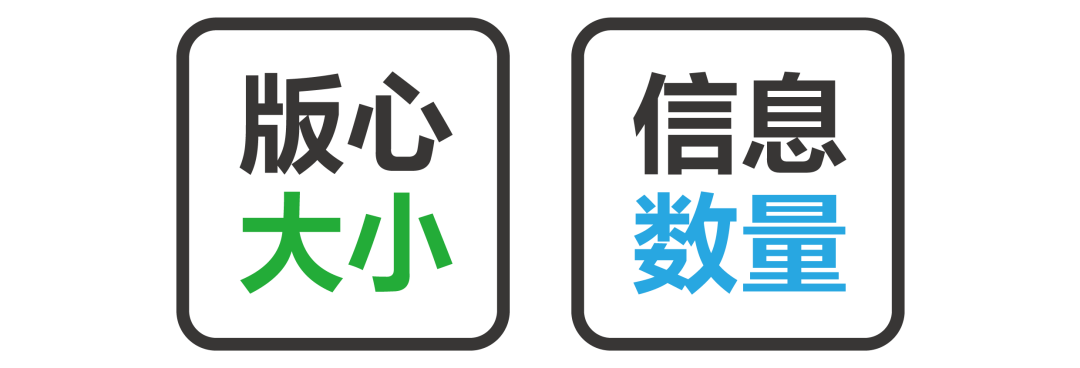
在我们订阅号之前的文章中提到过这样一个观点:版面是承载信息的一个载体。而一个版面承载信息的数量,完全取决于版心的大小。想要放下大量的信息,版心一定要大。但到底要多大才合适呢?
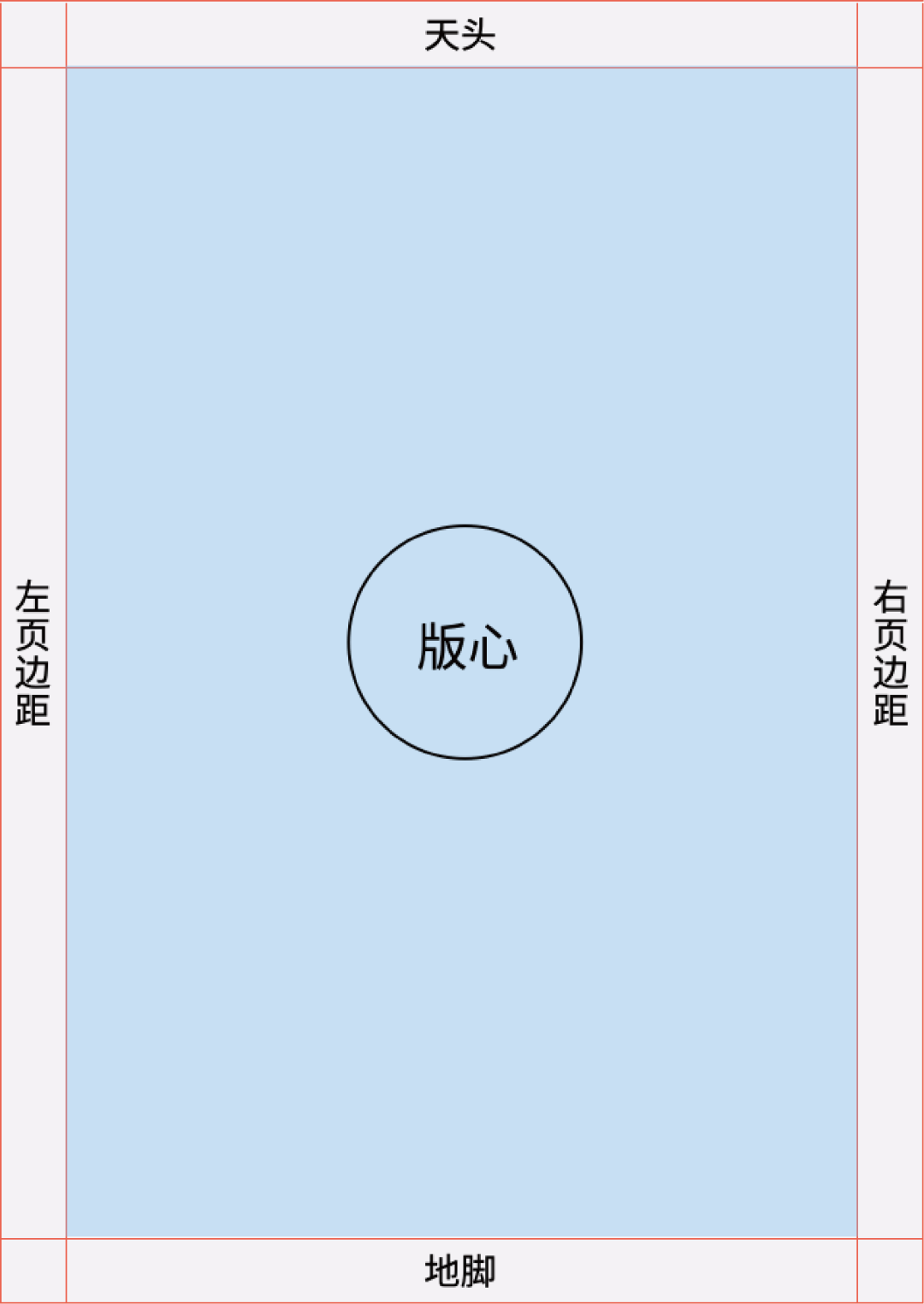
除去天头地脚、左右页边距以外,剩下的空间就是版心所在的区域。也就是说确定好天头地脚,左右页边距后版心就被确定好了。
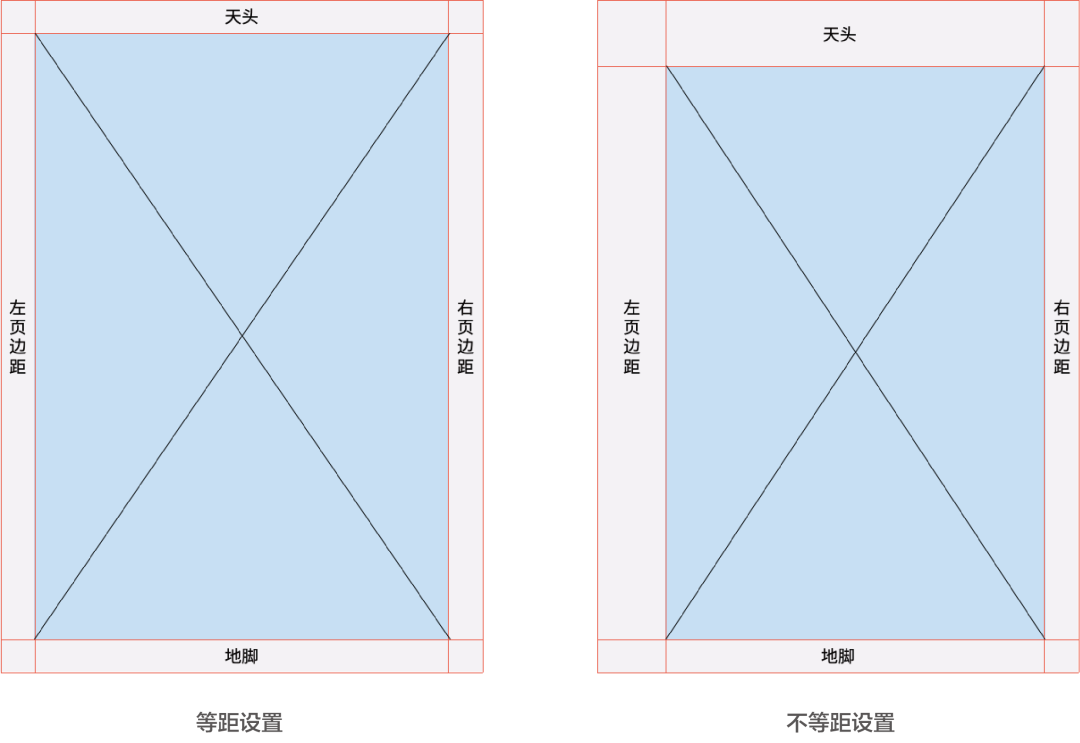
设定页边距的方式有两种,第一种是:等距设置,也就是天头地脚、左右页边距的大小都是相同的。第二种是:不等距设置,天头有可能大于地脚,左页边距也可能大于右页边距。而在这两种设置方法中,等距设置是最常用的。
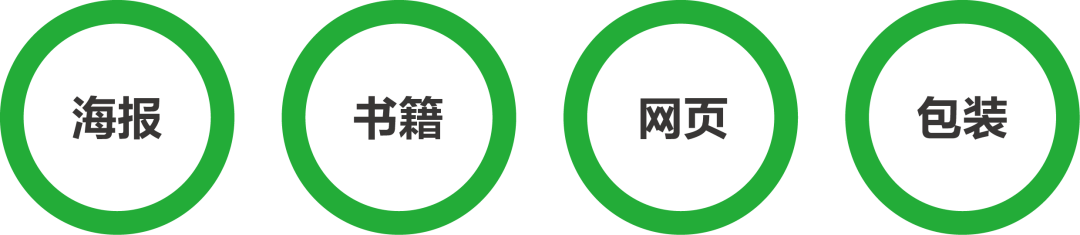
不管是在海报、书籍、网页还是包装中,等距设置都会让版面看起来非常稳定。所以在设定页边距时,四边的大小最好是一致的;尤其是左右页边距。因为,如果左右页边距设定的不一样,版面很有可能会出现重心不稳的情况。
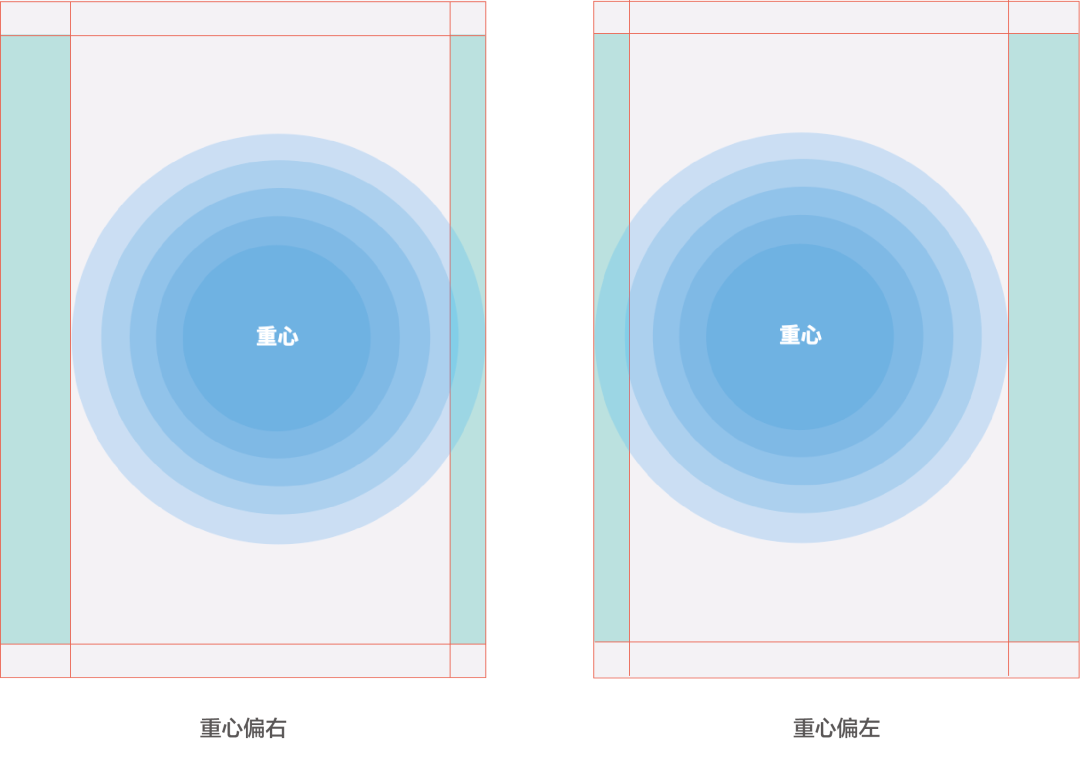
当左页边距大于右页边距时,重心可能会偏向右边。同理,当右页边距大于左页边距时,重心就可能会偏向左边。
不过存在即合理,虽然不等距设置会使版面重心变得不稳。但利用这个特性故意将天头地脚、左右页边距设置得不一样时,也能给版面带来动感。
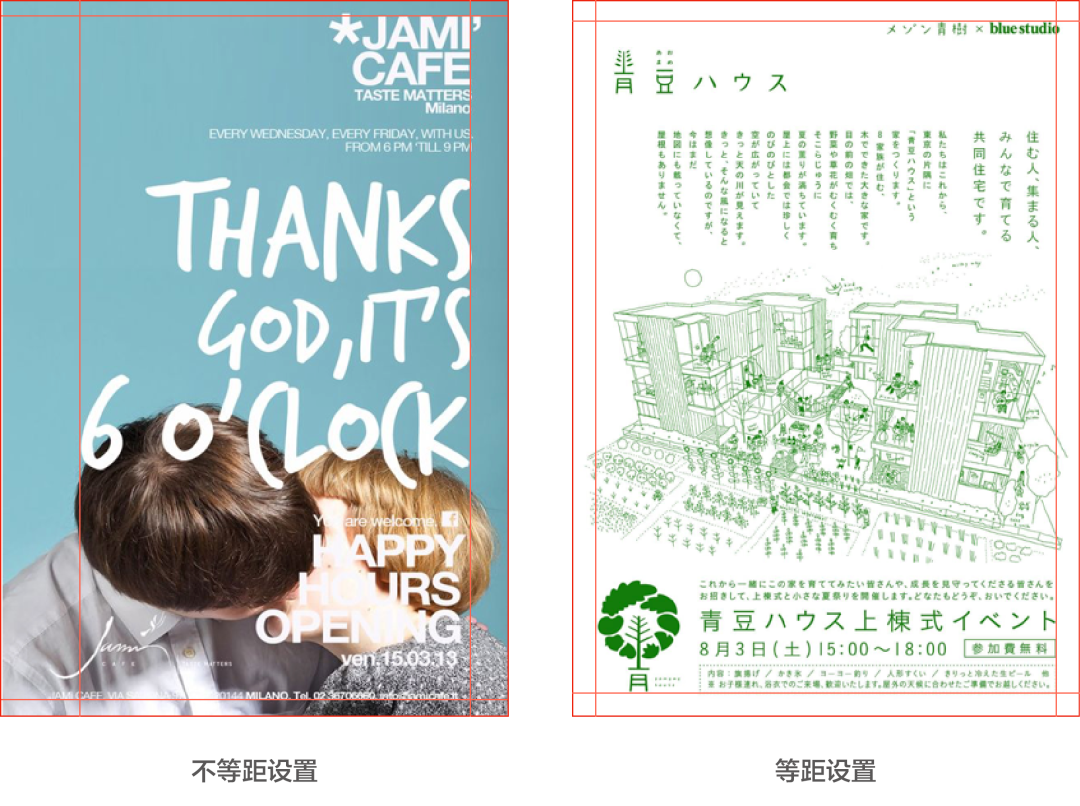
我们来看这组对比,左边的两幅海报明显是不等距设置,跟右边的等距设置相比,左边的海报少了四四方方的平稳感,却多了一些随意又轻松的活跃感。
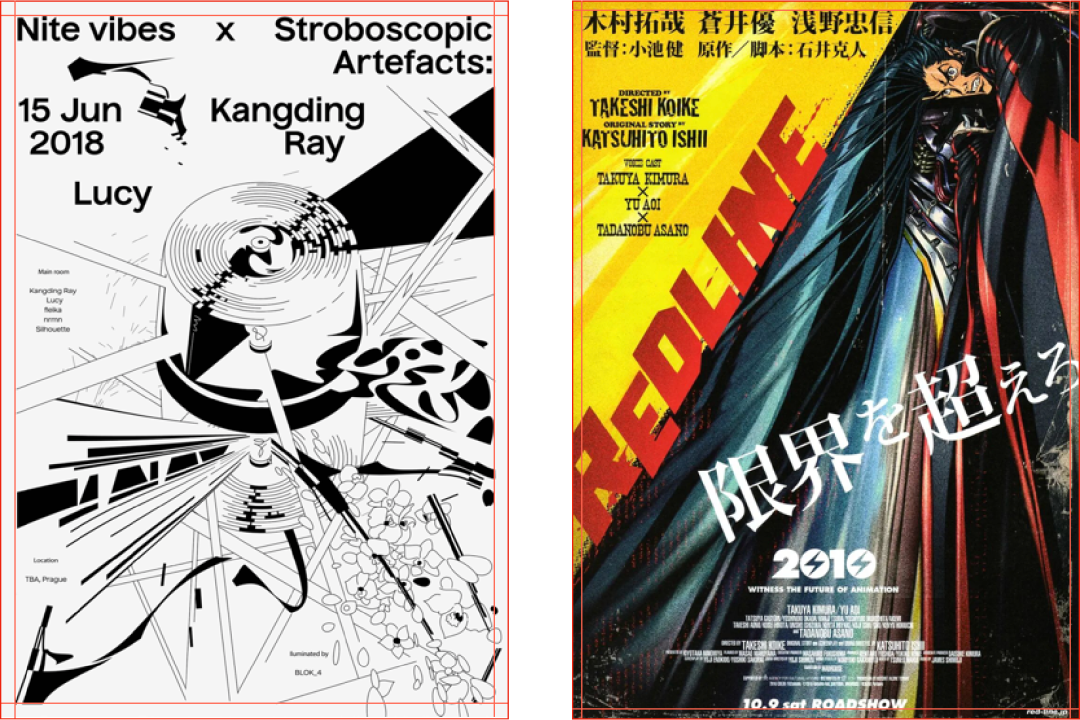
但是也不能以偏概全,因为即便是等距设置的版面也同样可以做出动感,比如现在我们看到的这些海报就是很好的例子。画面给人带来什么样的印象,取决于版面的编排方式,而不等距设置只是众多方法中的一种而已。
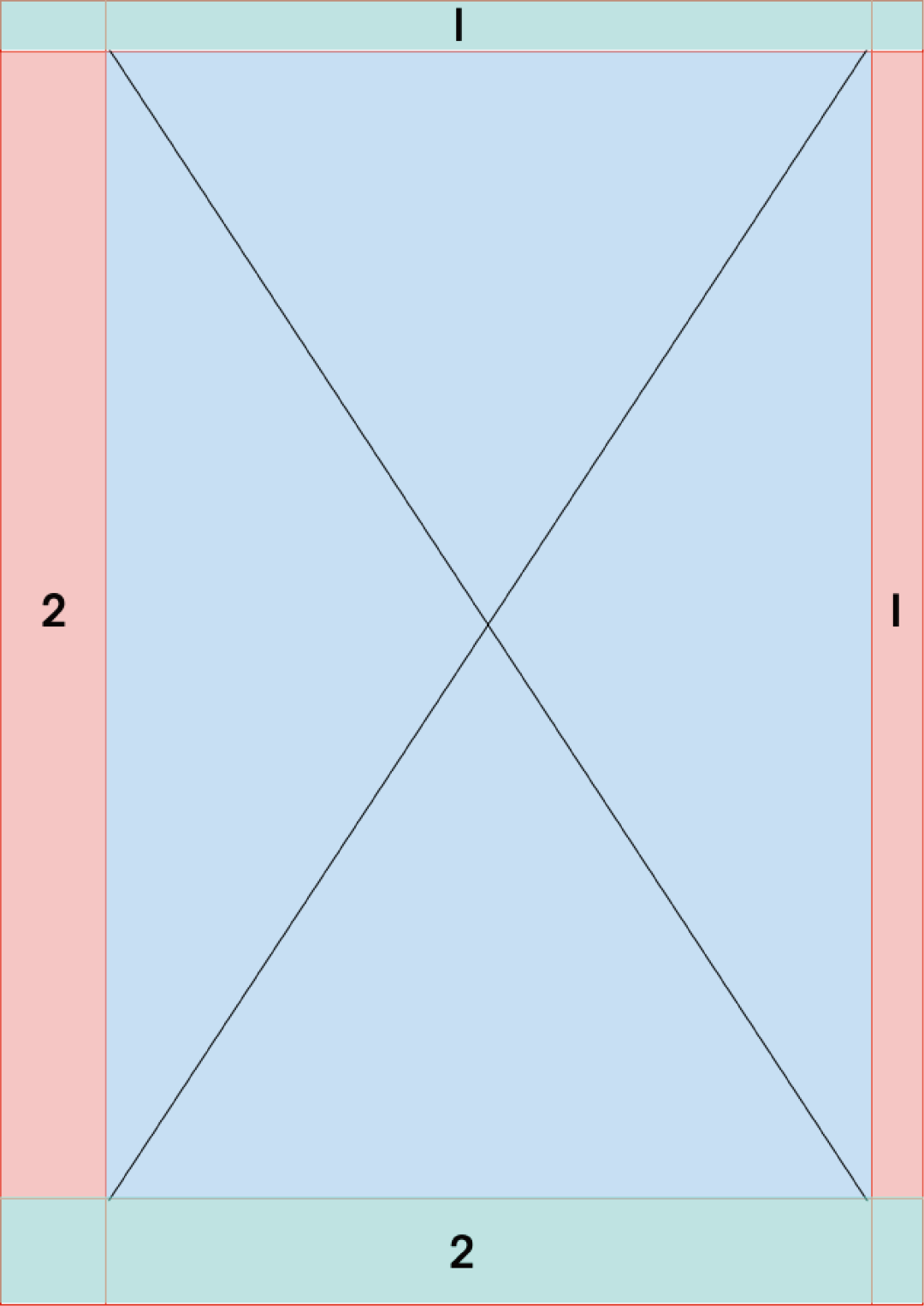
在实际操作中设定不等距的页边距时,可以用一个边的大小做参考,然后其他三边都与它呈一定的倍率关系。假设我们以天头作为参考,将它的边距设为为1,地脚可以是天头的2倍,也就是2。左页边距也可以是天头的2倍。右页边距可以是天头的1倍,也就是等于天头的大小。
虽然边距的大小可以自由设置,但是如果没有一个参考标准的话,一开始可能会无从下手,所以接下来我会根据不同尺寸的版面、文字数量的多少,列举出一些标准的页边距数值,供大家参考使用。当然在实际操作中,如果发现有不合适的地方,可以根据具体的需求来做调整。
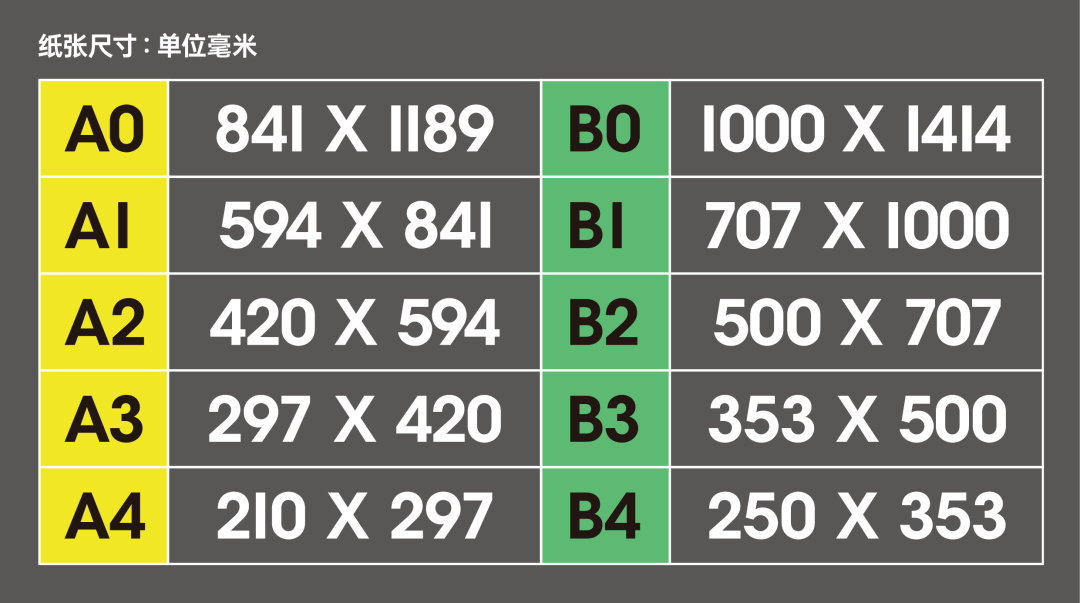
这是我们常用的纸张规格:A0-A4、B0-B4。有一点要跟大家说明的是,不管是从A0-A4还是B0-B4,它们只是纸张大小发生变化,而长宽比例是不变的。
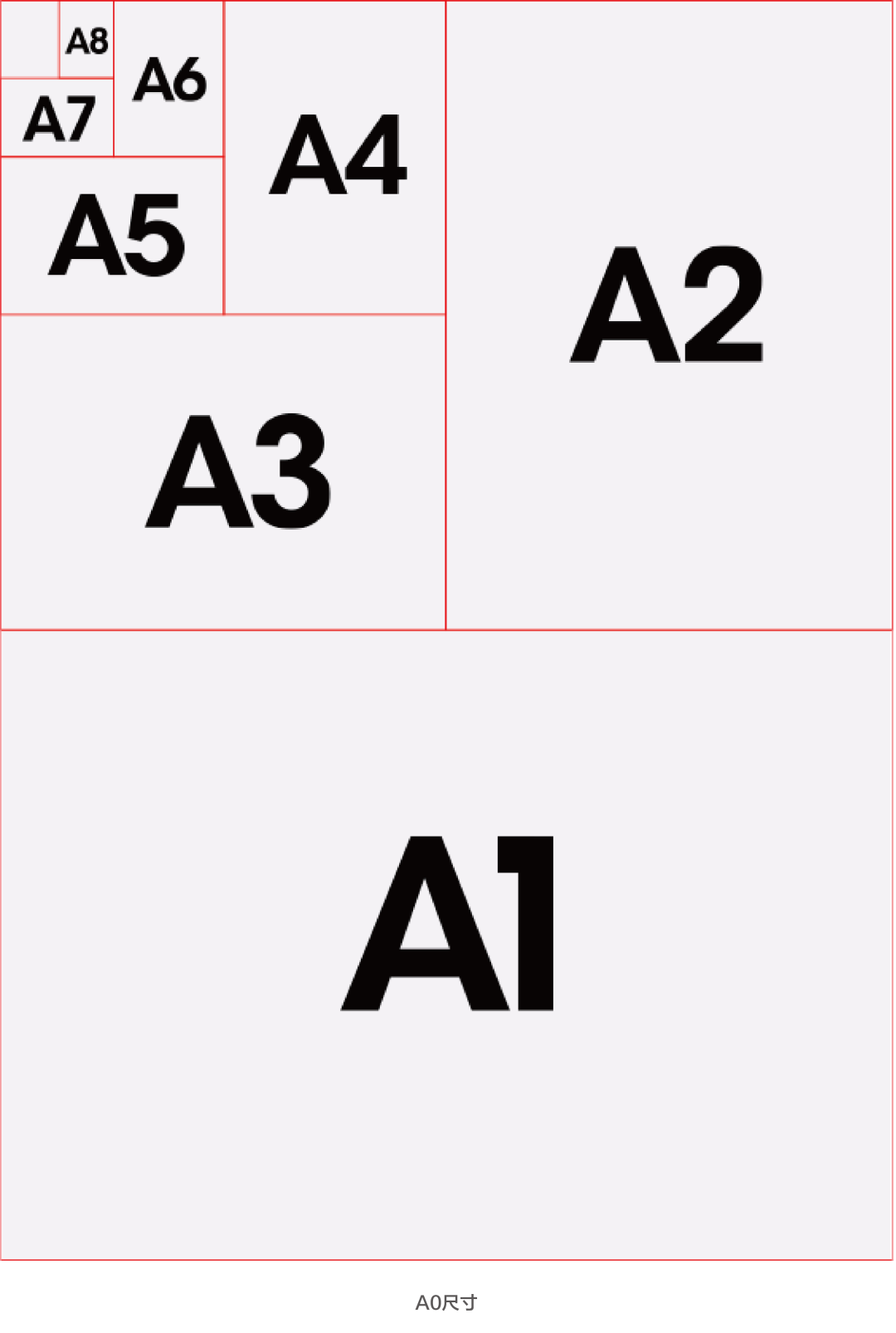
因为一张完整的A0尺寸的纸张,只要从长边的中点对开一次就可以得到两张A1,如果A1能够等比放大的话,还是一个A0的大小。后面的变化以此类推,我们常用的A4就是由A0对开四次得到的。
针对A0、B0尺寸的版面,信息量多时页边距可以设定在25~40mm之间;信息量少时页边距可以设定在40mm或40mm以上。
针对A1-A3、B1-B3尺寸的版面,信息量多时页边距可以设定在:7~12mm之间;信息量少时页边距可以设定在:12mm或12mm以上。
针对A4、B4尺寸的版面,信息量多时页边距可以设定在:7~10mm之间;信息量少时页边距可以设定在:10mm或10mm以上。
当信息量较少时,页边距的设定有两个选择:可以大也可以小。而当信息量较多时为了编排考虑,页边距只能设定的小一些,好为版心腾出空间来。
我们可以看上面这两张对比图,在同一个箱子里放置衣物时,左边的箱子非常凌乱而且明显装不下,而右边的箱子却非常整洁东西全都装进去了,因为右边的箱子是整理过后的。这是我想说的另一件事,在确定好版心后想要在其内部编排大量信息的话,首先要学会整理信息。
不知道大家在看我们之前的教程时,有没有注意到一个词叫「群组化」。我们在整理信息时,最简单又有效的手段就是「群组化」,将不同的信息按照类别来进行分组,这样就可以完成即容易理解又不会造成误会的设计。而且对文案信息进行分组既能帮到设计师,也能帮到观看版面的受众群体,为什么这么说呢?下面我们来说一下「群组化」的优点都有哪些。
在以上两个版面中,哪个版面内部的信息更易于理解呢?我相信很多人已经有判断了。跟左边的版面比,右边的版面元素分类明确,信息一目了然。
减少读者的获取信息的时间这一点这非常有意义。要知道一张招贴海报,它被阅读的时间只有几秒钟,如果我们设计师还故意给读者制造阅读上的障碍,这只会影响信息的传播效率。
还是之前那个例子啊,通过对比大家也可以看出,群组化后的版面阅读起来更为轻松,读者也能在最短的时间内获取更多的信息。因为群组化后信息是比较集中的,视线不用在版面上来回的跳跃,节省了这段时间阅读版面的速度自然会得到提升。
处理好留白问题,版面就不会显得凌乱,通过这个对比图就能看出,右侧版面经过群组化之后的信息更加清晰易读,留白部分也更加完整。
版面元素是彼此相关的,也是构成页面的主角。在编排时要刻意将存在关联的信息放在一起,这是群组化的基本原则。而这个原则也有一个名称叫做「亲密性原则」。
亲密性原则是由格式塔组织律中的邻近性原则转变而来的。说的是相互接近的元素比起相互远离的,更具有成组的倾向。利用亲密性原则,我们可以做到让页面内的信息排布疏密得当;元素与元素之间的联系即符合逻辑又满足视觉认知的要求,这大大的降低了读者在浏览版面时的视觉负担。可谓是版面编排设计的重中之重。
简单来说,亲密性原则就是将存在关联性的信息进行群组。但是要如何判断信息与信息之间,是否存在关联性呢?这也是我接下来要讲的重点了。我们就以一张展览海报中一定会出现的文案信息来举例子。
我将这些信息都拟人化了,目的也是为了让大家更好的理解,什么是亲密性原则。首先是小明的爷爷,他对应着标题,小明的奶奶对应着的副标题,小明的叔叔对应着标题或副标题的英文翻译,小明的爸爸对应着时间,小明的妈妈对应着地点,而小明自己对应着主办方、协办方等说明信息。
我们可以看到,标题和副标题可以成为一组,因为小明的爷爷和奶奶是夫妻关系,英文和时间信息可以成为一组,因为小明的叔叔和爸爸是兄弟关系,地点和主办协办信息可以成为一组,因为小明和他的妈妈是母子关系。这是最基本的一个信息分组方式,关系也很明确。接下来看看在实际的海报中,分组的方式都有哪些变化。
首先看这张海报,它的的分组方式是:将标题、副标题以及英文翻译归为一组,时间地点主办方等信息归为另外一组。我们通过家族体系表来看看,他这么分组的依据在哪呢。
通过家族体系表我们发现,他的分组逻辑是这样的:小明的爷爷奶奶本就是一组的,再加上叔叔也很合理,因为他们之间是亲子关系。而时间地点和主办方成为一组,它们分别对应着小明和他的爸爸妈妈,同样也是亲子关系。
再来看看这张海报的分组方式是什么。设计师将标题和副标题组合在了一起,而英文翻译单独存在,再接着就是时间地点主办协办方等信息。
通过家族体系表我们发现,这个分组方式和上一张海报的非常类似,唯一的区别在于英文翻译独立存在了。这就引出了分组时要注意的第一个要点:
接着看这张海报的分组方式:标题独立存在、副标题也独立存在,英文翻译和时间地点等信息成为一组,没有主办协办方等信息。
之前也说过了,存在关联的信息既可以成组也可以分离;所以标题、副标题独立存在没有任何问题,那英文翻译为什么可以和时间地点成组呢?因为,小明的叔叔和爸爸是兄弟关系,小明的爸爸和妈妈是夫妻关系。但是这里我们要注意,即使是互相存在关联的信息也存在着强弱之分。这就是在分组时要注意的第二个要点:
在看一下原海报,我们也可以发现这个特点,即便是在同一个组内,英文翻译与时间地点之间还是有一定距离的。
我们再看这张海报,它的分组方式有点特殊了,设计师将标题副标题、时间地点、主办方等信息分成了一组,英文翻译独立存在。
之所以这么分组,依据在于小明的爷爷和奶奶本就是一组的,而小明的爸爸和他们之间是亲子关系,小明与他的爸妈之间也是亲子关系的。所以可以将标题副标题、时间地点、主办协办等信息全部划分在一个组合内,但要注意好关系之间的强弱之分。英文翻译单独出现理由前面已经说过了就不再赘述。
最后我们再来看看这张海报,设计师将所有的信息都整合在了一起,这又是什么分法呢?
因为他们都是一家人,彼此之间都存在关联性,因此将所有的信息组合在一起也同样是合理的。
说完分组的方法后,再来说说组合数量的问题吧。在这一组的海报中,从左至右,文字组的数量逐步递增,随着组合数量的增加版面的编排难度也在增加,组合的数量越多版面的编排难度也就越高,所以大家在分组时千万不要贪多,那会给你的版面规划带来困扰。
通过距离我们能判断出,一个版面中到底存在有多少个组合,因为离得越近越有成组的倾向。
值得一提的是组合也有大小之分,一般大组合中都会包含几个小组合。因为,所谓的大组合就是由这些小组合组成的。
我们单独来看上面这张海报中的大组合,发现里面包含许多小组合,这些小组合之间也都存在距离,这个距离就是「组间距」。
组间距的大小由亲密性原则控制,关系越亲密组与组之间的距离也就越小。但这个距离是有个度的,离得近不代表就要挨在一起,离得远也不代表就要彻底拉开。
为了方便大家理解组间距的设定方式,我们看一下下面这个例子。
这个组合它的组间距是怎么设定的?是随意摆弄的吗?肯定不是。设定组间距是有方法的,比如关系较为亲密的信息之间,间隔的距离可以参照小字号文字的字高。
在这个组合中小字号的文字有三组,我用蓝色标出。
我挑选了这组文字作为参考。因为它的大小适中,用它能避免信息与信息之间发生粘连。而关系较为疏远的信息之间,间隔的距离则可以参照大字号文字的字高。
在这个组合中最大的字号就是中文标题了,我选择用它作为参照,那些间隔较大的距离就是这么设定的。
仔细看大家能发现,我并没有百分百严丝合缝的去卡字高,因为没有必要这么做,知道一个大致的距离就可以了。如果你就是想严丝合缝的对齐上也没问题。
如果出现因信息量较多,导致像上图这样无法设置组间距时该怎么办呢?这个时候我们可以使用「相似原则」或者「闭合原则」来解决这个问题。
相似原则,即彼此相似的元素容易被认知为一个整体,如:色彩相似、形状相似等等。
拿色彩相似来说,运用的方式非常简单就是最基本的换色。通过给文字组换上不同的色彩来进行区分。
色彩相似是换色,同理形状相似就是换字体。各个字体的外形都不一样,给文字组换上不同的字体,是可以起到区分作用的。不过,这需要设计师对字体有较深入的研究才能做好。
因为不同字体混搭在一起,稍有不慎就会导致版面看起来非常凌乱,字与字之间仿佛在打架非常不和谐。总的来说我更推荐大家使用色彩相似,操作难度低且容易出效果。
闭合原则就是通过框选的方式来进行分组的。被框在一起的元素容易被认知成一个整体。
比如这张海报,就是通过框选的方式进行分组的。
如果不想进行多个框选的话,还可以像这样单纯使用线条来进行分割,同样能起到闭合的效果。
这是为什么呢?格式塔原理大家都不陌生吧,我们在之前的文章中有专门讲过,用格式塔原理中的封闭原则就可以解释这一现象。
我们看左边的图形时第一眼感受到的,除了三条线段以外还有一个圆形。因为我们的视觉系统,强烈倾向于看到完整的物体,以至于大脑能将一块空白的区域解析成一个图形。
上面这张海报就是一个很好的例子,去除掉文字后我们能明显的感受到,版面被线段裁切成了5份,而每一份都是一个独立且封闭的图形。
讲到这大家还记得开篇处那位同学的问题吗:“当文案信息较多时要如何编排,版面看上去才能美观一些”。其实之前讲的所有理论部分,都是给编排部分做铺垫用的。因为只有当确定好版心以及整理完信息后,我们才需考虑要编排问题。另外我还附带了一个内容,那就是图片数量对版式的影响。
为什么要加这个内容呢?因为,我们在编排版面的时候不光要排文字还要排图片,图片数量不同对应的编排方式也有所不同。下面就给大家介绍一下,针对信息量较多图片数量又不同的版面,都有哪些编排的方式。
排法一:图文穿插。信息量多,图片数量在4张或是4张以上时,我们可以使用图文穿插的手法。
它的表现形式就是图片或是图形,与文字信息相互穿插排列。用这种相对活泼的方式可以用来缓解阅读大面积文字时所产生的压力。
图文穿插可以分为:规则型与不规则型两种。
报纸我们都知道,它是用来承载大量信息与图片素材的一个载体,它就是一个很好的规则型的例子。
其中最值得我们借鉴的,就是早期报纸的编排方式。将不同的文字组安排在划分好的区域内,然后用框或是用线来区分文字组。这是属于有规则的图文穿插形式,讲究的是秩序美。
不规则型的图文穿插,跟规则型比起来更为灵活多变。不过难点在于,需要设计师有较强的编排功底才能驾驭。
排法二:图字叠压。信息量多,图片数量少时可以使用图字叠压的手法。因为是叫图字叠压,所以图既可以叠在字上,字也可以叠在图上。
首先,我们来看看图叠字的表现形式。手法非常简单,就是图片叠压在文字在上方,而被叠压的文字大多都是标题或者标题的英文翻译。在实际操作时有一点要注意的是,我们要确保被压住的文字能被识别出来,也就是说叠压的幅度不能太大。
如果遇到因叠压幅度太大,导致文字无法被识别出来时,大家可以试试在图片的上方,再叠压一层描边后的文字;运用这个方法能使被压住的文字恢复一些识别性。
字叠图和图叠字一样,就是位置转换了一下而已。图叠字要注意的是文字,而字叠图要注意的就是图片了;在运用字叠图时,要记住文字不能挡住图片最吸引眼球的地方。
比如人物类图片不能遮挡面部,因为我们的视觉习惯已经决定好了,第一眼看的就是脸;除了脸以外还有眼睛,这也是不能被遮挡的。
如果图片没有特别吸引眼球的地方,就可以不用考虑遮不遮挡的问题。像这种常见的物体类图片;可以随意叠压,因为这类图片并没有非常突出的地方。
还有当图片充当底纹用的时候,也可以随意的进行叠压。
最后一个排法:文字叠压。文字信息量多且无配图时,可以使用文字叠压的手法,也就是文字与文字之间进行叠压。为什么没有图片时要使用这个手法呢?因为面对空无一图的版面时,受众的阅读欲望是非常低的。这时版面中就需要有一个亮点来吸引受众的视线,而字叠字就是用来创造亮点的手段。
在使用字叠字时也分两种形式:一、文字充当底纹;二、为了保证文字的识别性而使用的正片叠底。充当底纹大家都懂,那什么是正片叠底呢?
当两组相互叠压的文字,填充了对比色或是互补色时,为了使双方的识别性都不受到影响,就会使用图层混合模式中的「正片叠底」选项。正片叠底后文字被遮挡的部分就会浮现出来,这就是正片叠底形。
关于图字叠压中的「图叠字」以及文字叠压中的「正片叠底」,推荐大家去看看我们订阅号之前出过的这两篇文章,里面会有更加详细的讲解。
文案信息包括:标题信息、标题翻译信息、作者译者信息、卖点信息、以及装饰信息等5大部分。下面为大家拆解一下这些信息都有哪些合理的分组逻辑。
前三个部分描述的是:书名、书名的翻译、以及这本书的作者和译者,它们是可以成为一个组合的。
接下来卖点信息部分,它主要描述的就是这本书的概况,也是对书名的一个补充。总的来说所有卖点信息都和标题有关系,但关系的强弱之分我已经标明出来了,从卖点1到卖点4。而在这四个卖点中与标题关系最近的就是卖点1,也就是说能和标题单独成组的只有卖点1,因为它最简洁有力就像广告语一样。因此,如果其它三个卖点想要和标题成组的话,那也一定要带上卖点1,而不能脱离卖点1与标题单独成组。
最后就是装饰信息部分,它就是作为装饰存在的属于「有用的无用信息」,说它有用是因为它能解决一些版面中的负空间问题,比如说版面中有个地方显的很空,需要有元素来填补一下,这时就可以用上它。而说它无用是因为这类信息在版面中的字号大多偏小,读者基本都会忽略它们的存在。
我将所有的文字信息分成了9组,这个分组数量是属于偏多的,依据就是「存在关联的信息可以成组也可以分离」。
这是要用到的图片素材,一共有6个。
这本书籍的开本接近于a4大小,当信息量多时,页边距的宽度可以设定在:7~12mm之间,而我这次设置的是6mm,与参考值差了1mm。这也是之前说过的要根据实际情况调整,所谓的标准数值就是一个参考。
定好版心后,首先沿着页边距的中间处,也就是3mm的地方拉一个矩形出来,书脊处也要,这个矩形就是用来整合那9个组合用的。
先将第一个标题组合编排出来,位置放在右上角。为什么要放在这里呢?因为当文字竖排时我们的阅读顺序是:从上至下从右至左的。标题组合内部的组间距大小我参考了英文翻译的字宽。
接着在标题文字组的左侧,拉两根辅助线宽度为6mm,然后在中间处添加一根与标题组合一样高的线条用于区分。
然后再根据标题组合的高度,将组合2、组合3以及组合4一同编排出来,它们之间的间隔也都是6mm,同样用线区分。到此上半部分就编排完成了。
紧接着在上方组合的底部拉两根辅助线,宽度依然是6mm,然后添加一根线用于区分。之后将组合5编排出来整个横跨版面,它的作用就是分割上下空间。
继续添加一根线条用于区分,然后根据上半部分组合的结构,将下半部分的组合编排出来。编排完成后版面中还留有一块空白区域,这块空白区域的作用,就是为了再放置一组与标题组合做呼应的信息。
这组信息我选择了重复标题的英文翻译以及作者的英文名。因为是和标题组合做呼应用的,所以多少要和标题挂钩。同时为了削弱重复内容的印象,我故意换了字体,将之前的衬线体换成了无衬线。组合呼应上之后呢,色彩也要呼应上。挑选些重要的信息填充上与素材相同的色彩就可以。
在下半部分的组合中间添加好线条用于区分,方式与之前一样。最后将书脊编排出来第一个案例也就完成了。
第二个案例的组合数量比第一个少了两组,其中最后一个组合,我几乎将所有的卖点信息都汇聚在了一起。而这一大块信息我会放在腰封处,最后大家会看到一个有疏密对比的版面。
图字叠压适合图片少时使用,所以图片素材我会用标蓝的这两个。
页边距跟上一个案例一样还是6mm,版心定下来后接着将网格绘制出来,腰封我选择占横向上的双栏网格暂且用蓝色块代替。
第一步还是先将标题编排出来,然后在对角处编排第二个组合,组合2与标题做对角呼应。组合2内部的组间距参考的是英文翻译的行距。这也是我之前没有提到的,在没有小字号的情况下可以试试用行距来作为参考。
右上与左下角编排完成后,接着将左上与右下角的信息给编排出来。基本上所有的组合,都是按照网格来进行布局的,包括图中标蓝的文字组,它对齐的是隐藏网格。
这个隐藏网格就在横向第一栏的四分之三处,我用蓝线标出的位置。
接着把组合3编排在版面上方最吸引眼球的地方,因为组合3是一个很重要的卖点信息,我打算着重强调一下。它的位置关系是和卖点3作底部对齐的,到此整个书封的上方部分也就编排完成了。
剩下的就是将腰封处编排出来,也就是组合7整个卖点部分。这个大组合内部的组间距设置,参考了卖点2信息的字高。文字信息编排的差不多了,接下来我们将作为底纹的图片素材置入进版面中。
现在看着发现文字的识别性有点差,而且整个图片素材因面积和色彩的关系,显得非常跳跃很是抢眼必须要削弱它。
解决的方法就是给背景填充一个与图片色彩同属于同色系的颜色。
再把腰封标出来,恢复腰封处文字的识别性。最后在版面的上方挑选一些信息填充上白色,与腰封的色彩做一个呼应,而腰封处也要挑选一些信息填充上橙红色,与书封整体的颜色作一个呼应。最后的最后将书脊编排出来第二个案例也就完成了。
最后一个分组的方式跟之前那两个案例不同,只分了三组。
页边距以及网格依然沿用第二个案例,唯一不同的是我将腰封的位置往上提了半格,因为腰封处我打算编排更多的内容。
第一步,先创造出视觉焦点,对标题与标题的翻译使用正片叠底的手法。将组合3也就是装饰信息编排在标题组合的负空间处,右侧再添加一个卖点信息用于完善标题组合,使标题组合更丰满一些。
接着将剩余的卖点3以及作者译者等信息,分别编排在标题组合的上方与下方后,整个标题组合才算是刻画完成了。
我们来看看整个标题组合内部的组间距是怎么设定的:卖点3与作者译者信息,跟标题之间的间隔距离为一个字高的大小。
给腰封填充上橙红色,让暖色成为主色调。因为这是一本关于肉类的书籍,在没有图片素材的情况下,我想通过色彩来唤起读者对肉类的想象。
换完色彩后,将腰封处的信息都给编排出来,而整个腰封组合内部的组间距,则参考了卖点2信息的字高。
最后还是老套路,挑选一些重要的信息换上色彩作呼应,再将书脊编排出来,最后一个案例也就编排完成了。